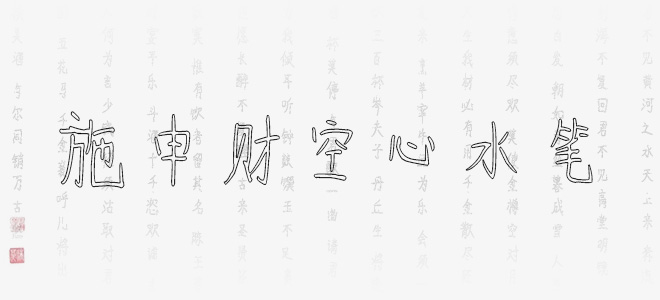
施申財(cái)空心水筆是一款極具個性的空心藝術(shù)字體,字體線條粗細(xì)適中,筆畫隨性,結(jié)構(gòu)灑脫自在,具有很好的視覺感,適合于文化類的宣傳設(shè)計(jì)、商業(yè)類品牌的廣告和產(chǎn)品包裝設(shè)計(jì)以及個性化文字排版等較多場景。
施申財(cái)空心水筆